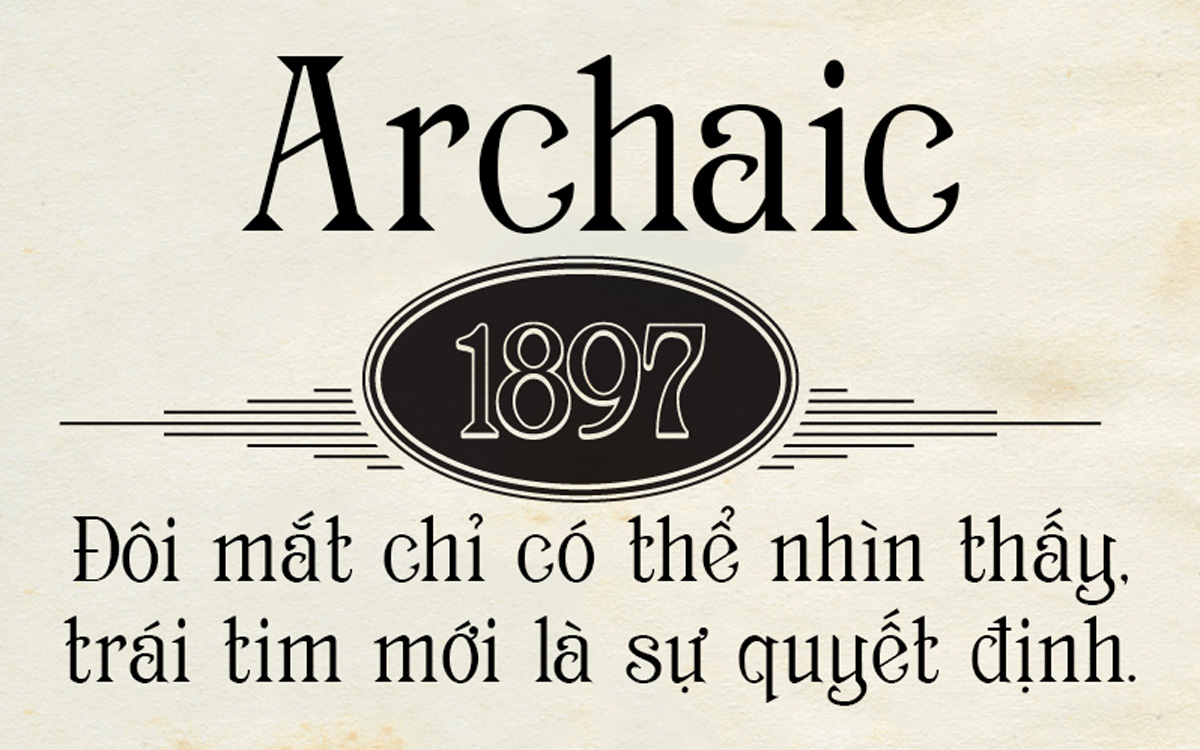
SVN-Archaic 1897: Font Chữ Thanh Lịch, Sang Trọng Cho Thiết Kế Thiệp Cưới, Thời Trang & Tạp Chí
Khám phá SVN-Archaic 1897 – bộ font chữ thanh lịch, hiện đại và sang trọng bậc nhất. Lựa chọn hoàn hảo để nâng tầm các thiết kế thiệp cưới, nhận diện thương hiệu thời trang và ấn phẩm tạp chí của bạn.
Trong thế giới thiết kế đồ họa, typography (nghệ thuật chữ) chính là “linh hồn” của mọi ấn phẩm. Một bộ font chữ đẹp không chỉ truyền tải thông điệp mà còn khẳng định đẳng cấp và phong cách của thương hiệu. Nếu bạn đang tìm kiếm một font chữ thanh lịch, hiện đại và sang trọng, thì SVN-Archaic 1897 chính là “mảnh ghép” hoàn hảo mà bạn không thể bỏ qua.
1. SVN-Archaic 1897 Là Gì? Sự Giao Thoa Giữa Cổ Điển Và Hiện Đại
SVN-Archaic 1897 là một bộ phông chữ (typeface) được thiết kế với độ tinh xảo cao, mang trong mình vẻ đẹp vượt thời gian. Giống như tên gọi “Archaic”, bộ font này lấy cảm hứng từ những đường nét cổ điển của thế kỷ 19, nhưng được tinh chỉnh, gọt giũa để mang đậm hơi thở đương đại.
Sự kết hợp giữa những nét thanh – nét đậm uyển chuyển và tỷ lệ chữ cân đối giúp SVN-Archaic 1897 toát lên một vẻ ngoài cực kỳ quyến rũ, cao cấp và không bao giờ lỗi thời. Đặc biệt, với tiền tố “SVN”, đây là phiên bản đã được Việt hóa chuẩn mực, giúp các designer thoải mái sáng tạo với tiếng Việt mà không lo lỗi dấu.
2. Ứng Dụng Đỉnh Cao Của Font Chữ SVN-Archaic 1897
Nhờ vào đường nét tinh tế, bộ font này có tính ứng dụng rất cao, đặc biệt tỏa sáng trong các lĩnh vực đòi hỏi tính thẩm mỹ khắt khe:
Thiết Kế Thiệp Cưới Sang Trọng
Một tấm thiệp cưới là lời mời trang trọng và lãng mánt nhất. SVN-Archaic 1897 mang đến cảm giác:
Lãng mạn & Tinh tế: Các ký tự được uốn nắn nhẹ nhàng, tạo cảm giác bay bổng cho tên của cô dâu và chú rể.
Đẳng cấp: Phù hợp với các concept đám cưới mang phong cách Fine Art, Minimalist (Tối giản) hoặc Classic (Cổ điển).
Nhận Diện Thương Hiệu Thời Trang
Ngành công nghiệp thời trang (đặc biệt là thời trang cao cấp – High Fashion) luôn khao khát những đường nét tối giản nhưng đầy quyền lực.
SVN-Archaic 1897 cực kỳ hoàn hảo khi dùng làm Logo, Lookbook hay Tagline cho các thương hiệu thời trang, trang sức, mỹ phẩm.
Font chữ toát lên sự đắt tiền, thanh lịch và tạo được dấu ấn mạnh mẽ ngay từ cái nhìn đầu tiên.
Dàn Trang Tạp Chí (Editorial Design)
Trong thiết kế tạp chí, đặc biệt là các ấn phẩm về phong cách sống, nghệ thuật hay kiến trúc, typography đóng vai trò dẫn dắt thị giác người xem.
Sử dụng SVN-Archaic 1897 cho các Tiêu đề lớn (Headline) hoặc Trích dẫn (Quote) sẽ tạo ra một trang layout đầy tính nghệ thuật.
Khoảng cách các chữ (kerning) được tính toán kỹ lưỡng, mang lại cảm giác thoáng đãng, dễ đọc nhưng vẫn đầy tính đương đại.
3. Tại Sao Designer Nên Sở Hữu SVN-Archaic 1897?
Tối ưu hóa tiếng Việt (Việt hóa 100%): Các dấu câu được thiết kế tỉ mỉ, đồng bộ với phong cách gốc của chữ, không bị lệch pha hay gãy nét khi gõ tiếng Việt.
Đa dụng và linh hoạt: Dễ dàng kết hợp (font pairing) với các font chữ Sans-serif (không chân) cơ bản để tạo ra sự tương phản thú vị trong thiết kế.
Tôn vinh sự tối giản: Không cần thêm thắt quá nhiều họa tiết, bản thân dòng chữ được viết bằng SVN-Archaic 1897 đã là một tác phẩm nghệ thuật.
4. Tổng Kết
Nếu bạn đang đảm nhận một dự án cần đến sự thanh lịch, hiện đại và sang trọng, đừng ngần ngại chọn SVN-Archaic 1897. Từ những tấm thiệp cưới lãng mạn, những cuốn tạp chí nghệ thuật cho đến các bộ nhận diện thương hiệu thời trang cao cấp, bộ font này chắc chắn sẽ giúp thiết kế của bạn vươn tầm đẳng cấp.
Mẹo thiết kế: Hãy thử kết hợp SVN-Archaic 1897 (dùng cho Tiêu đề) với một font chữ không chân mỏng, hiện đại như Montserrat hoặc Lato (dùng cho Văn bản phụ) để đạt được hiệu ứng thị giác tuyệt vời nhất!